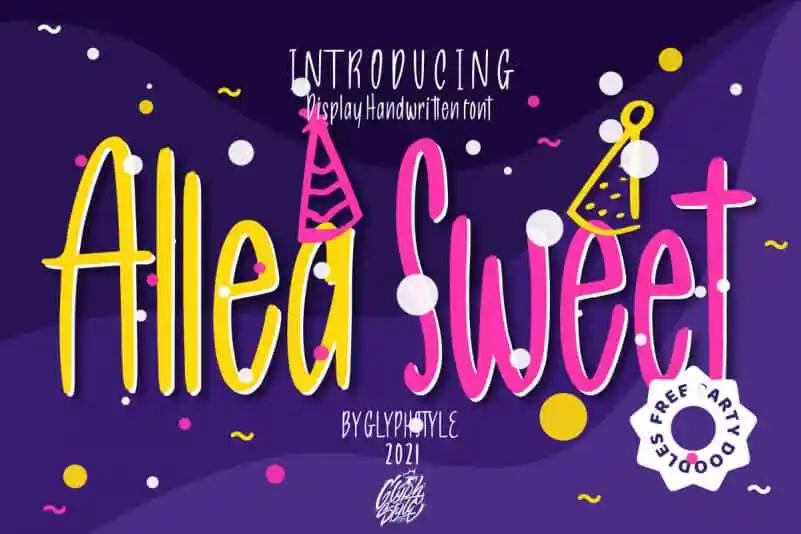
Allea Sweet Display Font – Download Grátis
A fonte Allea Sweet Display é uma elegante escolha para projetos de design que buscam um toque alegre e vibrante. Essa fonte foi criada usando técnicas manuscritas, tornando-a não apenas fácil de ler, mas também uma grata surpresa em termos de visual. Além disso, você recebe o Doodles Party como um bônus perfeito para projetos infantis ou eventos temáticos. Este super-cute font é ideal para criar design leve e encantador, seja para festas de crianças ou projetos divertidos dirigidos a crianças. Com Allea Sweet Display Font, transforme qualquer projeto em uma verdadeira celebração da vida!